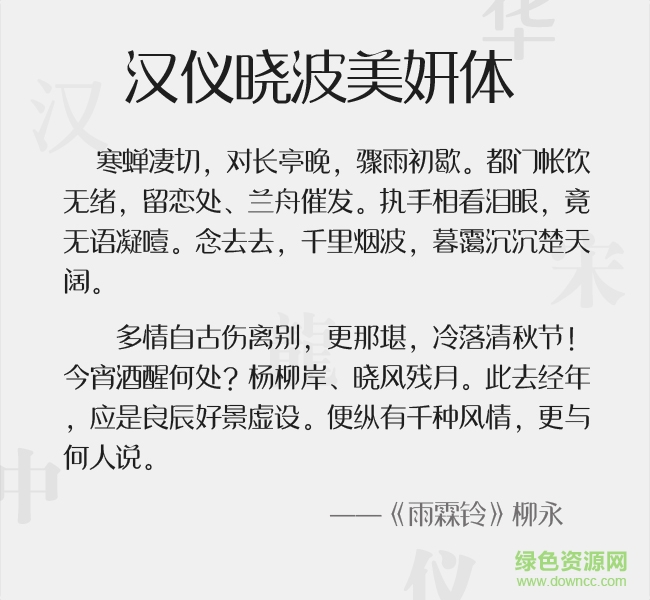
漢儀曉波美妍體是一款漢儀類圓滑優(yōu)美風(fēng)格字體軟件,曉波美妍體部分筆畫一筆而過,顯得非常圓滑,整體效果給人很清爽完美的感覺,還有更多好看字體歡迎來綠色資源網(wǎng)下載體驗(yàn)!
漢儀曉波美妍字體是一款商業(yè)字體,角度自然,空間比例完美,從橫筆到圓弧再到撇一筆帶過,輕盈飄逸,細(xì)節(jié)精致,順暢圓滑!